お世話になってます
最近お世話になっている「ものたち」を記念撮影です!
これは取り外し可能な携帯電話を入れるケースです。
革で出来ていてステッチがかわいいバッグ型なんです。
ストラップはついているものの、カバンの底に沈んでいたりすると
引出すのが大変…。布とかじゃないのを探していたら見付けました!
取り外しが簡単なので、バッグを変えてもすぐにつけられます。
ジーンズにもつけられます。旧型携帯なのでちょっと太っちょ…新型にすれば、もっとスリムだから他にもパスネットとかも入れられそうです。
ソニーのネットワークマンも必需品!
常に音楽やFMを聴いています。
連続時間が長いのが気に入って買いました。
しかしコードが長いのでいつもカラマンボーで難儀でした…コードは2回も銅線が切れかかって交換しています。
ポケットに突っこんでいるので、コードを引っぱっちゃうのがいけないんですよねぇ・・・。そんな迷える子羊たちの救世主が!コードを自動に巻き取れるのが出たんですよ〜。
いや〜便利ですね〜。コードがカラマンボーなんて葬り去りました!快適です!フフフ!
以前はPCからの充電だったんですけど、これまた新しい機能・コンセントから直接充電できるような器械が出たのでそれ使ってます!mojitor-fさんのような美しい曲ならいいのですが、最近は
アルファとかいきものがかりとか…お気に入りはSUEMITSU&S THE SUEMITHでしょうか…。ちょっとノリが良すぎるかしら…。
mojitor-sさんも愛用していますが、
ほぼ日の手帖カバー革製を使っています。以前はナイロンのカバーだったのですが、革の方がしっかりしているので買い換えました。
中にたくさんポケットがついているので収納に便利です。あとは自分愛用のスケジュール帳を挟んで、小さくて青いボールペンはこの手帖のペンホルダーにぴったりです。何かのおまけでもらったのに大活躍です!
さぁ外出のお供に大活躍のこものたちです。
みなさんの便利グッズは何ですか?
ハーシーズのチョコカード
今年、アメリカの友人から届いバレンタインデーカードの封筒の切手を見たら、ご存知ハーシーズのキッスチョコのデザインでした。
エッー?こんな特定の商品のデザインが公共の切手に使われていいの?と驚きです。
それともこの形はもはやLOVEとKISSの表現として一般的なんでしょうかね〜
そして、この封筒に入っていたカードが、ハイ、こちら。
大きなHUGとKISSをたくさん頂いた様な気持ちで、嬉しいざんす
簡単なアイデアですが、これを実行に移すのには結構勇気が必要ですが、さらりとやってくれました。思わず笑みがこぼれるカードですね。
ハーシーズ(Hershey's)のキスチョコはなんでも100年の歴史があるそうですよ。今年は100年記念なんですって。だから切手もこのデザインらしいです。
このサイトを見るといろいろと書いてあって面白い。このキッスチョコは100年間ほとんど変らずに生産されたそうですが、第二次世界大戦の1942〜1949、この期間中だけ生産されなかったんですって。アルミフォイルが戦争の為に使われたかららしいです。ほんとかなぁ・・・
今はクッキーやアイスクリームも出ていますよね。食べたことないけど、どうなんでしょう。今はチョコといえばベルギーなどヨーロッパが主流ですが、たまには100年のアメリカの歴史の味を試してみるのもいいかもね。
なごめる文房具
ワンコの大好きなホネです。
いえ、ポストイットのケース、台湾土産です。ティッシュみたいにスルッと出せるんですね。
ただの四角とかではなくて、こんな遊び心がオフィスには大切ですよね!うん、作業場にも!家庭にも!
私はこういうケース入りのは使ったことがなかったので(いつもあちこちにポストイットが散らばっている・・・)ピュッと取り出せるのにも感動しました。中身もつめかえられるし、磁石つきなので留めておけるし、便利です。
「3M 利貼」って描いてありましたよ。「利貼」がPost-itなんですね。いいねいいね。
こちらはブタさん。じゃなくて、タコ糸です。え、お肉に巻く?
いえいえ、タコ糸は紙を切るときに使うんです!二つ折りした紙の内側にタコ糸をはさんでザッザッと切っていくんですよ。
この方法を以前YMCAのクラスで教えてもらって以来、とっても気に入って使っています。だからタコ糸は机の引き出しに入っているんです。
下のスタンプ押した紙の上辺みたいな味のある切り方になりますよ。アルファベットのスタンプ〜
イニシャルでいただいちゃいました!
ありがとうございます、愛用しておりますよ、mojitor-sさん!赤と青の色鉛筆。ビン型色鉛筆、と袋に書いてありました。コーラのビンみたいですね〜
上下切り離せるようになっています。子どもの頃、何色も重ねてつなげていくロケットみたいな色鉛筆ありましたけど似てますね。
ビン型の隣に写っていますが、私はわりと赤・青色鉛筆を使うんです。ちょっとなつかしの・・・という雰囲気ですが1本で2本分使えるところが好き。ですが、赤いほうだけなぜか、よく折れるのです。使う頻度によるものでしょうか。
にっこりしちゃうクリップもうふふ、いただきものです。
にっこりつながり、電話の子機の、声が聞こえてくるところ。説明書ににっこりの顔のかたちに穴があいていてなごめる、のようなことが
書いてあって笑っちゃいました。確かにこの顔みたらとげとげしい声は出せませんね。ではでは、おやつの時間でーす。
つんつく&のろりんぼう
去年のBrodyのWSで新しい試みをしました。
参加メンバーには2文字ずつアルファベットを与えられ、「各アルファベットにつき10種類以上デザインしてくること」という宿題が…。
当日集められたアイデア満載の26文字を一冊の本にまとめ、各メンバーに戻されます。そこから好きな文字を「親」としてAからZまで
作っていくというものです。左の図はWS当日に書いた自称「つんつく」という文字たちです。
全体に広がると何だか刈った後の芝みたいに「つんつく」している
のでそういう名前にしました。別にBrodyは名前をつけろとは言っていませんが、私は自分が創るものには名前をつけてしまう習性があるもので…。
しばらく放ったらかしにされていた「つんつく」ですが、スーパーカリ人mikoさんがHPでhttp://fuu-an.seesaa.net/すんばらしい世界を展開していて…あぁ〜これではイケナイ、イケナイ…と反省しました。「ごめんね…いけないお母さんを許して…
やがて「つんつく」は所々形を変えながら「固まれ〜」とか「踊ろう〜」とかポーズをとって
遊んでいます。良く遊び、良く眠るいい子に育つでしょうか…?
WSでは、二種類の異なった文字をハイブリッドするところまでが
課題でした。最後に無理やりくっけましたが、それは全く気に入って
いないので…まだ冬眠中です。
そのもう一方の文字がこの「のろりんぼう」です。
この子は「のんびり、まったり」脱力系です。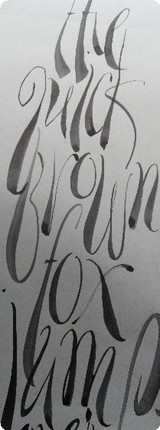
「お調子者で根っこが優しいつんつく」と
「のんびり、まったり、ゆるゆるのろりんぼう」は
母親の「我が道を行っちゃうもんね〜」という遺伝子を引継ぎながらどう成長していくのか…。
mikoさんとこは第三子、四子が登場だもんねぇ・・・。
楽しみ〜!!
雁皮紙の切り方
雁皮紙に書いてみようかな、と以前紙舗直で買った色つきの雁皮紙をゴソゴソ出してきました。
絹のようなツヤ!薄くてハリがあってすてき〜〜〜〜!
何もしなくても滲まないし、表面はスムーズなのでペンでもイケます。いい感じに書けて、フムフム結構満足。
でもね、紙を切るのが難しいのですよ。和紙は水切りすると、切り端がデックルエッジになっていいので、そうしようと思ってやったら、あららら〜
こんなんなっちゃいました。
どーしましょう。雁皮紙を上手に切れる方法、どなたか知りませんか?
他の色も書いて試したいので、これから紙舗直にお散歩がてら行ってこようと思います。(歩いて行けるってウレシイ)
お店で聞いてみれば良いですね。そうだ、なんでも親切に教えてくれるから、尋ねてみることにしま〜す。ほな、行ってきま〜す
2007年02月23日
使おう!使おう!
暖かい天候に感謝して外出もしやすいこの冬ですが、皆様は
どんな美術館へ行かれていますか?
公共の美術館も様々な工夫をしています。この工夫…?賢く
使うしかありませんね!!
だめですよ〜、入館して作品まっしぐら〜という意気込みも
わかりますが、見る前にいろいろ調べましょうね〜。
いちおう…(・◇・)(*^o^*)
あ・ら・カルチャーは、渋谷周辺でゲットできるかと思います。渋谷、恵比寿、原宿周辺のかるちゃーさんぽ地図が載っていて、かるちゃーに触れられる施設が紹介されています。また、これを持参
すると特典が受けられる施設の紹介もありますよ!
http://www.syabi.com/index.html
私は、東京都写真美術館がお気に入りなので、そこでこのパンフレットを入手致しました。
東京都写真美術館では、企画展の半券で2階のカフェ「シャンブルクレール」でコーヒーが100円引きになります。また、あ・ら・かるちゃーパンフレットを提示すると”店長おすすめコーヒー”注文の際にベルギーチョコ1個
サービスと書いてありますよ!今度試してみよう!
このベルギーチョコはなんとブリュージュからの輸入だそうですよ。
ブリュージュの空気を先に吸いたい方!行くべし!
それからこのカフェ(1階と2階にありますが、100円引きコーヒーは
2階のカフェです)は、ベルギービールも豊富だそうで、隠れた穴場らしいですよ。
最近は、この美術館の友の会に入ろうかいなぁ〜などと思案中です。
昔ボストンにいた頃、ボストン美術館の会員になっていました。企画展は無料だし、行く機会が多いなら特典があるのは魅力的ですよねぇ〜。
こちらは、東京芸術劇場のチラシです。http://www.geigeki.jp/saiji_002.html
まだ行ったことがないのですが、月に一度「ランチタイムパイプオルガンコンサート」があるそうで、無料で楽しめるそうです。
HPには以前のコンサートの模様も動画で見られますから雰囲気が
チェックできますよ。次回は3月15日(木)です。
他にもパイプオルガン講座とかも企画あるらしく面白そうですよ〜!興味のある方…要チェックです。
面テープで固定して、裏打ちの要
領ですね。
これは、表紙と同じ構造のものに試し用に貼った寒冷紗です。寒冷紗の際の処理をどうするかで
印象が変るので、際1ミリ、2ミリ、全部貼る、もしくは糸を抜いてフリジン?みたいにする…先生と相談して約1ミリの際処理に決定です!フリジンは可愛いのですが、考えたら本棚から出す度に
mojitor-fさんが形を整えなくてはならないかしら〜ってことで今回は却下…。
こんな際にはどう糊をつけるのか…?
じゃ〜ん!この裏技?です。
ある程度硬い板で薄いもの…今回は金属板に糊をつけて、寒冷紗の端っこに糊をうつしていきます。
刷毛でつけられない部分に糊を
つけるのはあの手この手を使いますねぇ〜。
最後に…何なんでしょう…この猫ちゃん…。
とても上品な姿をして…。
実は、製本教室に「お願いしま〜す」と言った時にこの姿
でした…。作業すること2時間半、終了後…。
「ありがとうございました〜」と挨拶をして外に出たら
…あらまぁ〜何とまだ同じお姿でした…。
置き猫? あっ、こっち見た!
今週は表紙と本体の合体です!上手くいきますように。